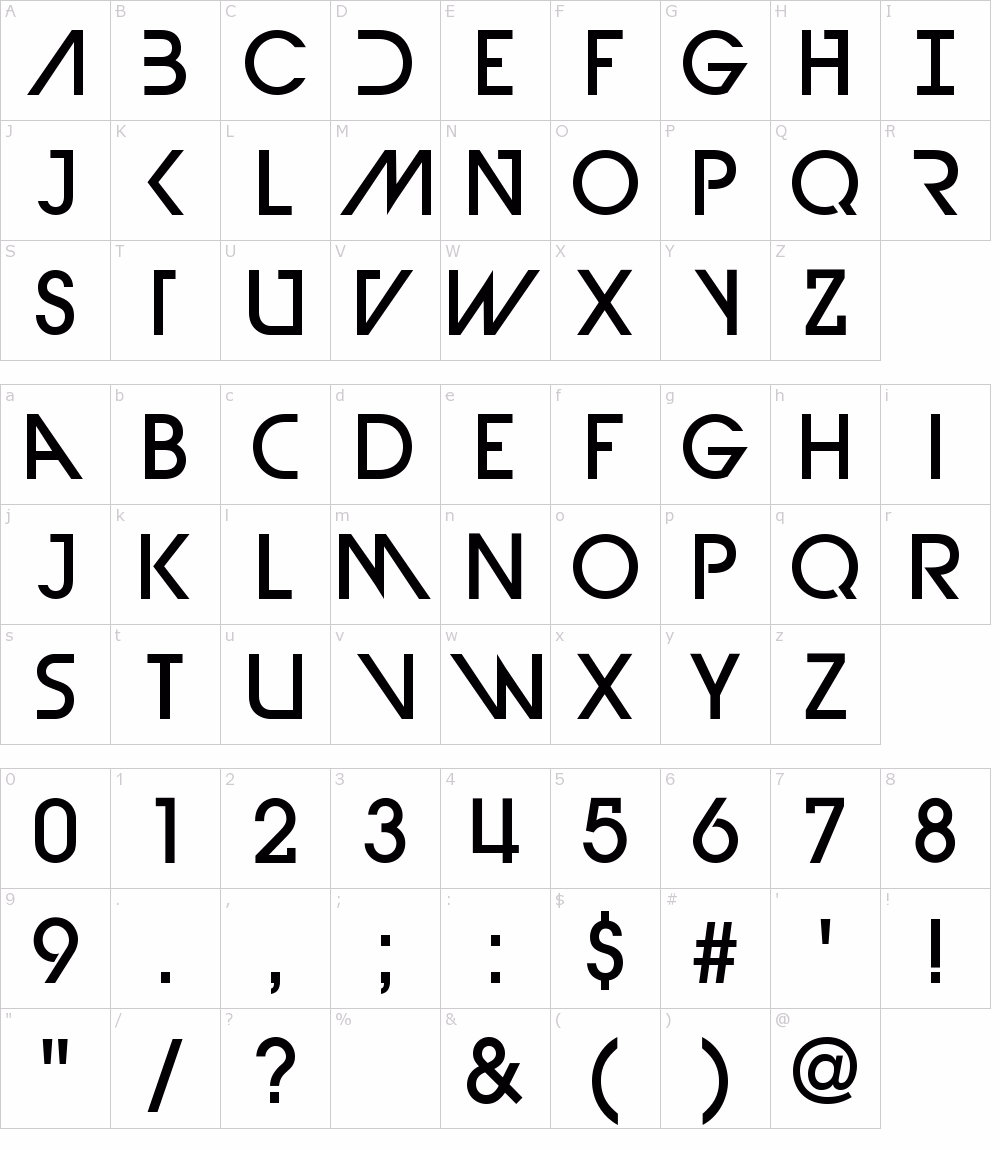
Guía Completa de la Fuente Devil Breeze Bold
En el vasto universo del diseño gráfico, la elección de una tipografía puede marcar la diferencia entre un proyecto memorable y uno que pasa desapercibido. Hay fuentes que son funcionales, otras que son elegantes, y luego están aquellas que irradian personalidad y energía. En esta última categoría, encontramos a Devil Breeze Bold, una tipografía que se ha ganado un lugar en el arsenal de muchos creativos por su estilo audaz y divertido. Creada por el talentoso diseñador Wesley Pastrana, esta fuente es la herramienta perfecta para quienes buscan inyectar carácter y dinamismo a sus creaciones. A lo largo de este artículo, exploraremos a fondo todo lo que necesitas saber sobre Devil Breeze Bold: desde sus características y licencia de uso hasta una guía detallada para su instalación y aplicación en tus programas favoritos.
DEVIL BREEZE..Was designed based on the variations and similarities of AVANT GARDE Typeface (created in the era of the 60s by Herb Lubalin and Tom Carnese). ENJOY!!! Paypal:  IF U WANT TO DONATE!!!
¿Qué es y Quién Creó la Tipografía Devil Breeze Bold?
Devil Breeze Bold es una fuente de tipo display, lo que significa que está diseñada principalmente para usarse en tamaños grandes, como en títulos, encabezados, logotipos y carteles. Su diseño se caracteriza por trazos gruesos y contundentes, con un aire juguetón y moderno que la hace destacar inmediatamente. No es una fuente pensada para largos bloques de texto, sino para captar la atención con pocas palabras.
El cerebro detrás de esta creación es Wesley Pastrana, quien opera bajo la firma Wesley Pastrana Rosado Weslo GFx. El trabajo de diseñadores como Pastrana es fundamental para enriquecer la comunidad creativa, ofreciendo herramientas que permiten a otros materializar sus ideas. Devil Breeze Bold es un claro ejemplo de una fuente con una intención clara: ser divertida, impactante y fácil de usar. La subfamilia "Bold" indica su peso; es una variante gruesa y robusta, ideal para asegurar que tu mensaje tenga la máxima visibilidad y presencia.
Características Principales y Estilo Visual
El estilo de Devil Breeze Bold es inconfundible. Sus letras combinan bordes ligeramente redondeados con una estructura sólida, lo que le da un aspecto amigable pero a la vez muy potente. Es versátil dentro de su nicho, funcionando bien tanto en contextos juveniles y desenfadados como en proyectos que requieran un toque de audacia.
Para entender mejor sus atributos, podemos desglosarlos:
• Impacto Visual: Su grosor la hace perfecta para titulares que necesitan ser el centro de atención.
• Personalidad Divertida: Evoca una sensación de energía, creatividad y modernidad. Es ideal para marcas o proyectos que no se toman a sí mismos demasiado en serio.
• Legibilidad en Tamaños Grandes: Aunque no es para párrafos, su diseño garantiza que cada letra sea clara y distinguible cuando se usa en encabezados.
• Conjunto de Caracteres: Incluye el alfabeto completo en mayúsculas y minúsculas, números y los signos de puntuación más comunes, lo que la hace bastante funcional para la mayoría de los usos de titulación.